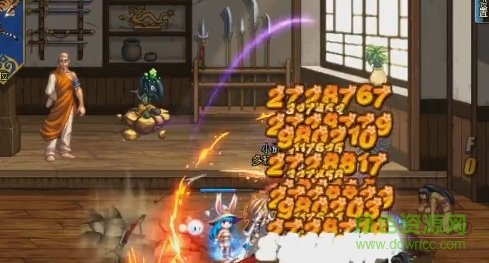
dnf桃花傷害字體是地下城游戲最新版本中推出的一款浪漫桃花字體,當(dāng)玩家對(duì)游戲怪物或他人造成傷害時(shí),就會(huì)出現(xiàn)桃花效果的數(shù)字顯示,十分穿衣盎然,喜歡的朋友就來綠色資源網(wǎng)體驗(yàn)吧!】
但經(jīng)過游戲大神的補(bǔ)丁提取,用戶可以更自由的使用該字體進(jìn)行展示了!